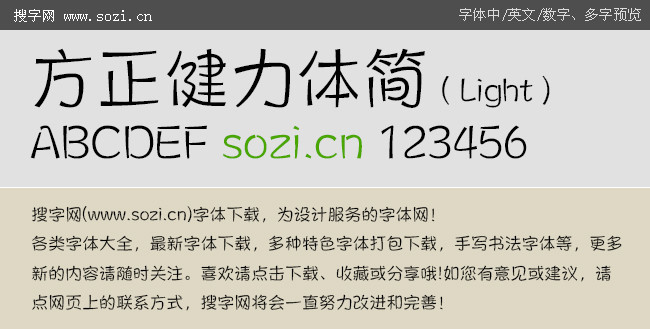
方正健力體簡(jiǎn)Light
搜字網(wǎng)提供一款方正健力體簡(jiǎn)中文字體下載,方正健力體是作者從某健身的標(biāo)志引發(fā)的靈感,點(diǎn),撇,捺,抅,橫,直劃等都是不同方向,也好像各種健身項(xiàng)目的不同表達(dá)方式一樣,是一款充滿動(dòng)感和活力的字體。適合健美行業(yè),活力飲料,運(yùn)動(dòng)服裝和運(yùn)動(dòng)鞋的廣告宣傳。